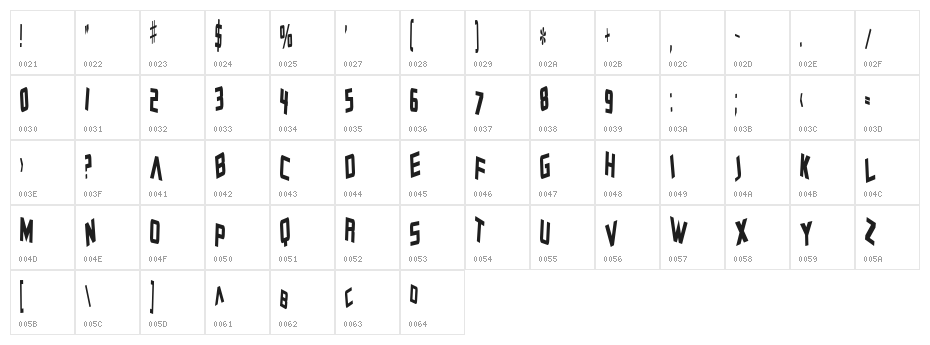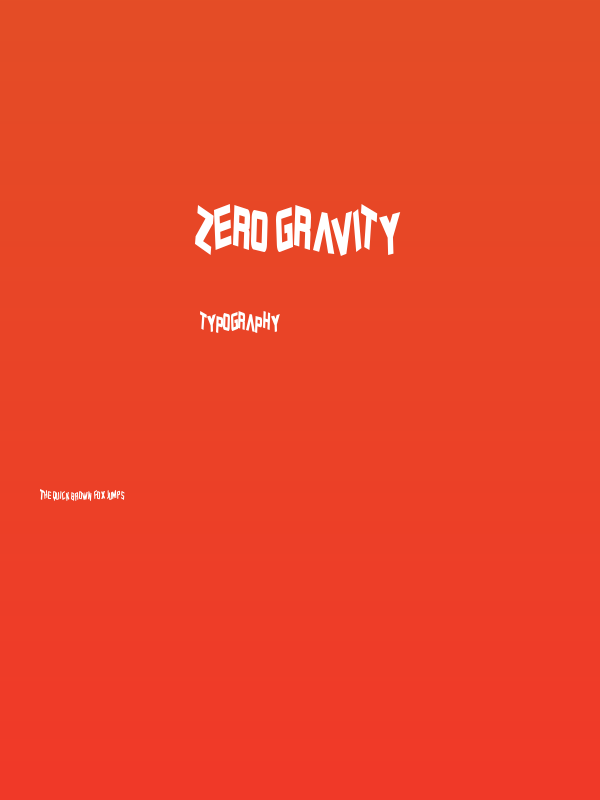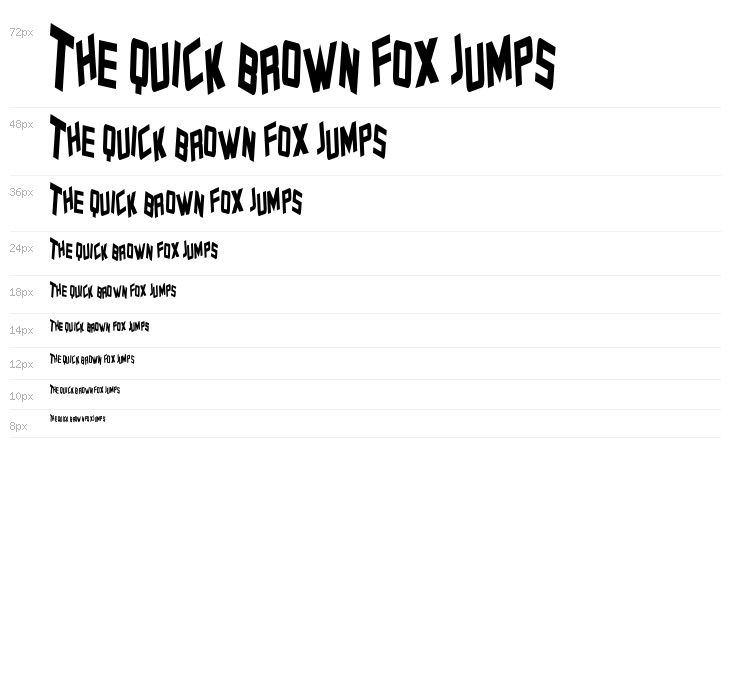
Zero Gravity Font
| Name | Zero Gravity |
| Kategorien | Quirky |
| Vorgeschlagene Projekte | Ideal for sci-fi themed posters, tech company logos, video game titles, and modern branding projects. |